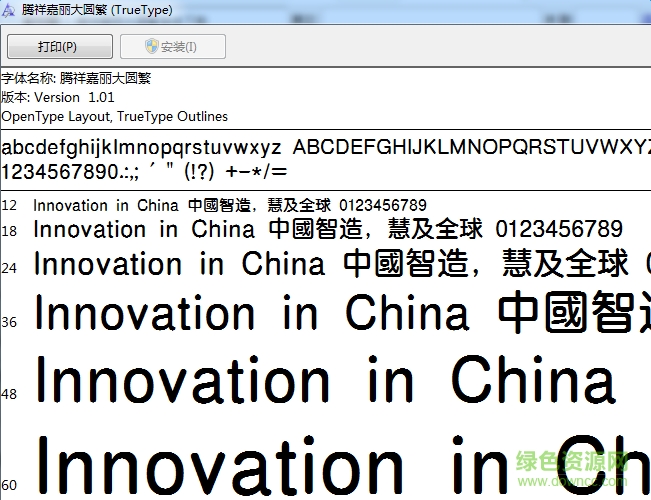
騰祥嘉麗大圓繁字體是一款超好用的個(gè)性繁體中文字體,該字體可以廣泛應(yīng)用于廣告設(shè)計(jì)、宣傳海報(bào)、ppt、影視制作以及任何使用文字的領(lǐng)域,有需要的朋友可以免費(fèi)下載收藏。
騰祥嘉麗大圓繁字體是一款極具個(gè)性的字體,該字體十分飄逸,彰顯了自己的個(gè)性,有喜歡的朋友可以來綠色資源網(wǎng)下載使用!